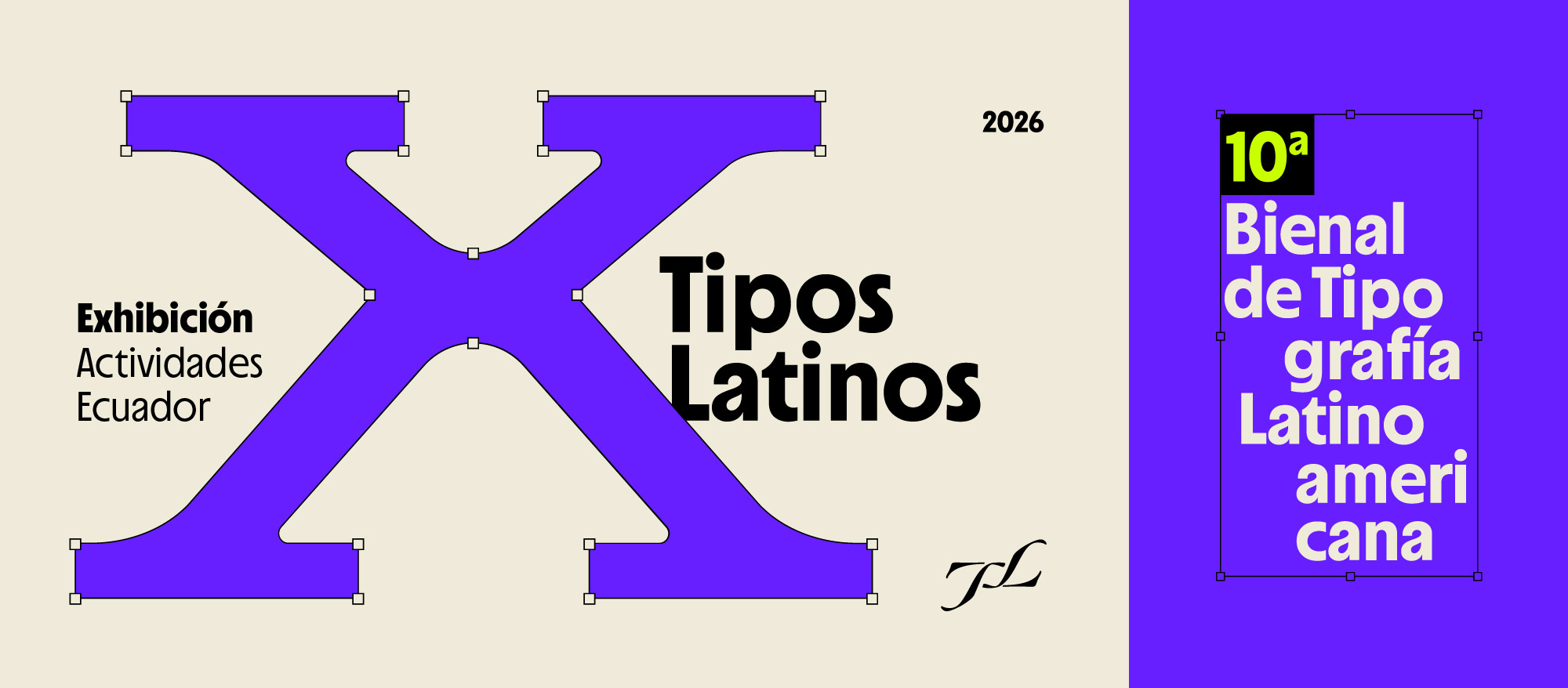
Exhibición y Actividades Tipos Latinos 10 en Ecuador
⇒ Charla 1:
Stratto, café con letras
por Alejandro Rodríguez
Una conversación sobre el cruce entre café, identidad y tipografía, y cómo el lenguaje visual puede convertirse en parte de la experiencia de un producto. Desde su tienda en Quito y su trabajo con café de autor, compartirá cómo utiliza la tipografía para comunicar el origen, carácter y personalidad de cada café. https://www.instagram.com/stratto_bodegadecafe/
⇒ Ceremonia de Inauguración Exhibición Tipos Latinos 10
Inauguración TL 10 – Quito, Ecuador
La 10ª Bienal de Tipografía Latinoamericana Tipos Latinos llega a Quito para presentar los 75 proyectos seleccionados y las 3 Constancias de Excelencia de esta edición. La muestra reúne una mirada diversa sobre el momento actual de la tipografía en América Latina, después de un proceso que recibió 768 proyectos de toda la región y cuya jura presencial se realizó por primera vez en Ecuador.
En el marco de los 20 años de Tipos Latinos, la inauguración en Quito abre un nuevo ciclo de exhibiciones que llevará esta selección a distintas sedes de América Latina, celebrando dos décadas de creación, intercambio y desarrollo de la tipografía latinoamericana. En exhibición hasta diciembre 2026.
⇒ Taller:
Del glifo al sistema
por Isabel Peña
En el marco de la 10.ª Bienal de Tipografía Tipos Latinos Ecuador, este taller propone un acercamiento introductorio y práctico al diseño tipográfico a través de la construcción de un sistema de letras, desde la ideación y el boceto hasta la digitalización de caracteres clave en Glyphs. No se requiere experiencia previa. https://www.instagram.com/isapg7
Un taller práctico para conocer el origen y contexto del Estilo Chicha y aprender sus principales trazos caligráficos utilizando pincel de punta chata. Los participantes explorarán el alfabeto de la A a la Z y aplicarán lo aprendido en una composición propia, acercándose a un lenguaje gráfico inspirado en la cultura popular latinoamericana. https://www.behance.net/saraarguello
Inauguración exhibiciones, Contraforma: Carteles Tipográficos y EPB X: 10 años de carteles
Por los 10 años de Ecuador Poster Bienal nos unimos para gestionar la apertura de 2 muestras en una misma sala. Contraforma: Carteles Tipográficos, una exhibición curada en conjunto por Tipos Latinos Ecuador y Ecuador Poster Bienal, que reúne una selección de obras internacionales pertenecientes a la colección histórica de la EPB. Esta muestra pone un énfasis en la tipografía como herramienta, lenguaje y forma de comunicación visual.
Además, celebramos el décimo aniversario de Ecuador Poster Bienal con EPB X: 10 años de carteles, una exhibición especial que presenta carteles conmemorativos creados por diferentes artistas internacionales en homenaje a esta primera década de trayectoria. Ambas muestras estarán en exhibición hasta mediados de diciembre de 2026 en el ala Norte del CAC.
⇒ Caminata:
Ruta Tipográfica
Centro Histórico, Quito
Un recorrido a pie desde el Centro de Arte Contemporáneo por las calles del Centro Histórico de Quito para observar, identificar y registrar letras, símbolos y signos presentes en el paisaje urbano. Una invitación a descubrir la tipografía que habita la ciudad a través de rótulos, fachadas, inscripciones y otras expresiones gráficas que forman parte de su identidad visual.